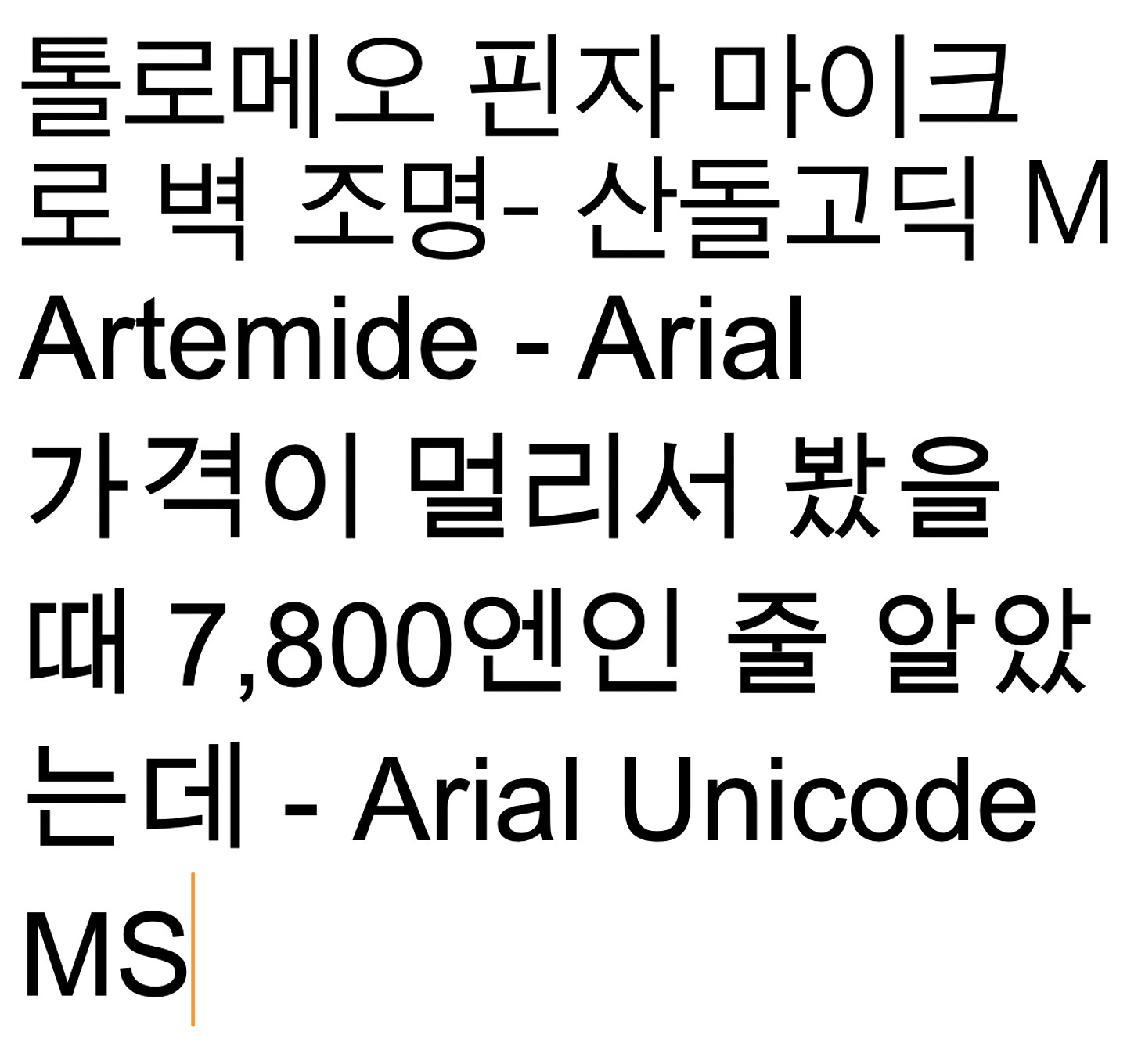
이런 길쭉한데 고딕스러운 폰트 이름이 뭘까요? 비슷한거라도 아시는 분 ㅠㅠ +영문폰트도 궁금해요
산돌고딕 L
1. 영문 폰트 : Arial입니다. 영문 폰트이고 PC OS에 기본 탑재되어 있습니다. 2. 한글 폰트 1(톨로메오…) : 산돌고딕(1995년 출시)입니다. 유료 폰트이고, 산돌구름에서 구매하실 수 있습니다. 3. 한글폰트 2(가격이 멀리서...) : Arial Unicode MS입니다. PC OS에 기본 탑재되어 있습니다.